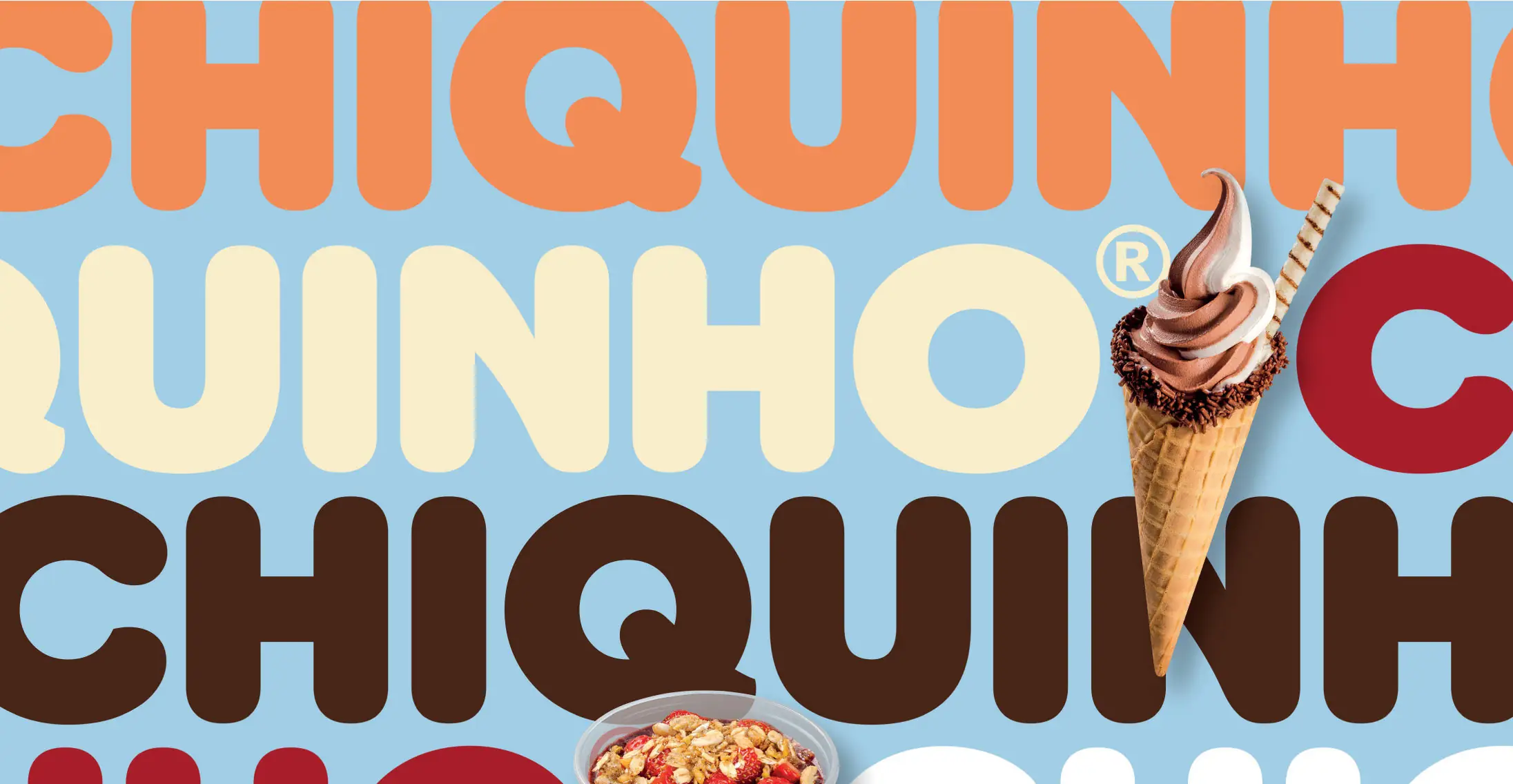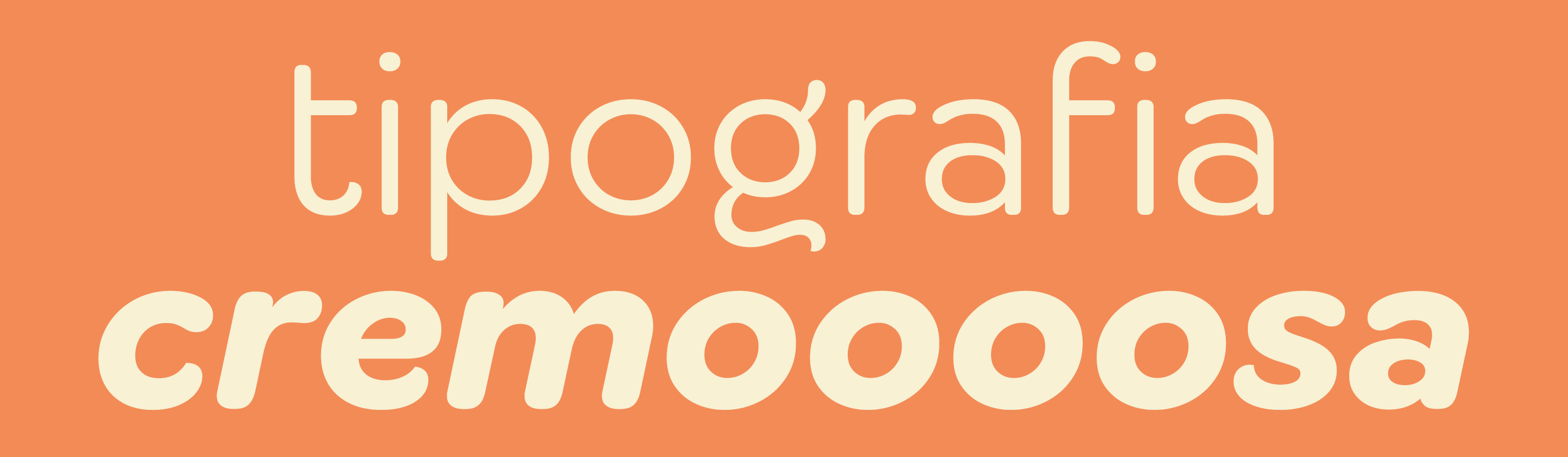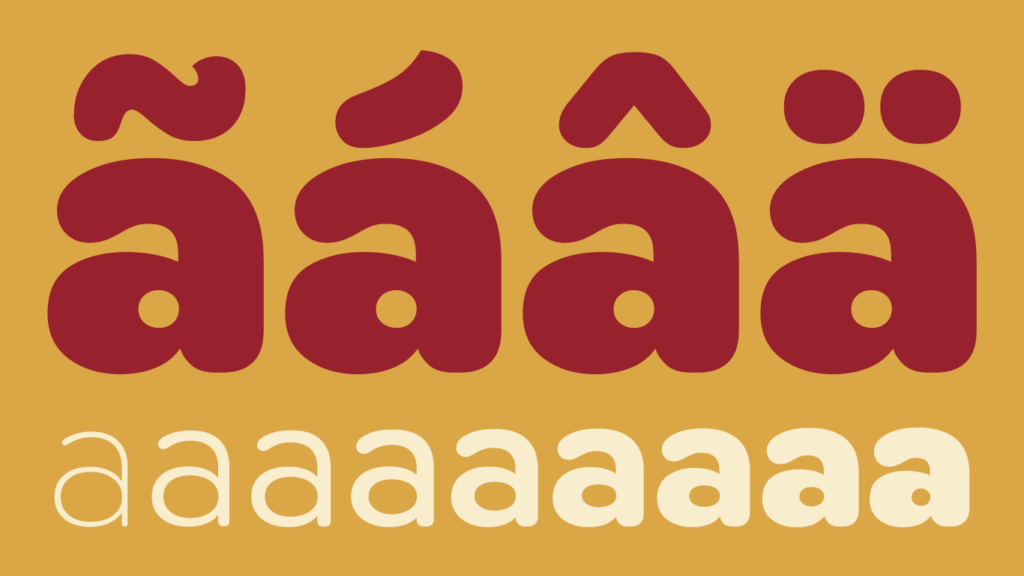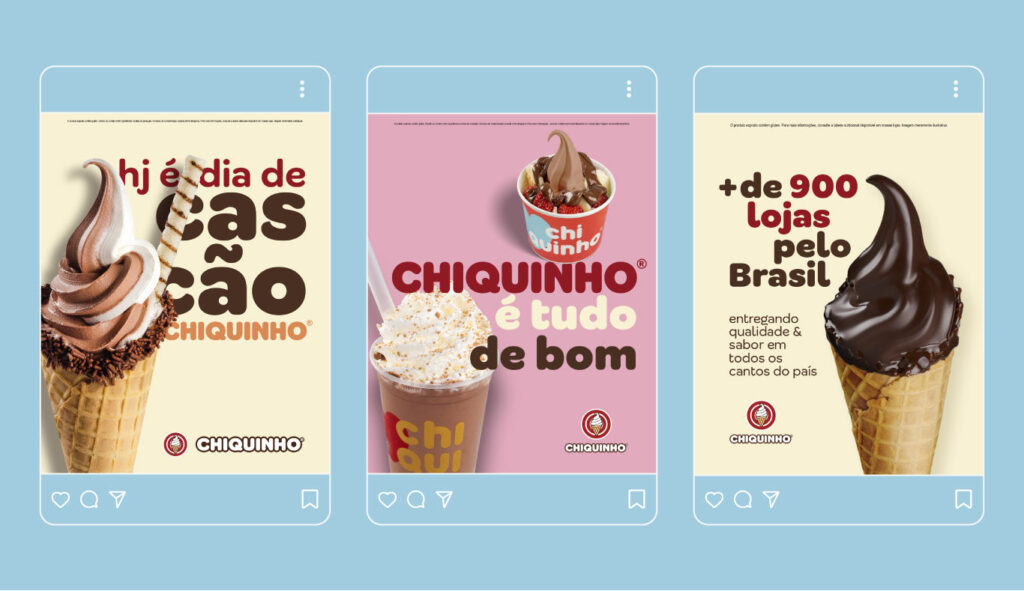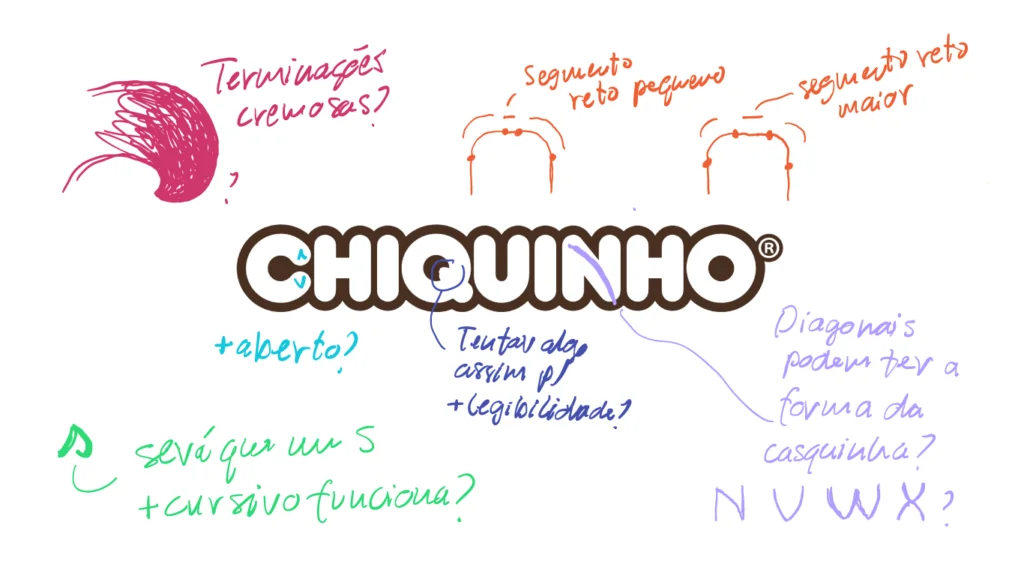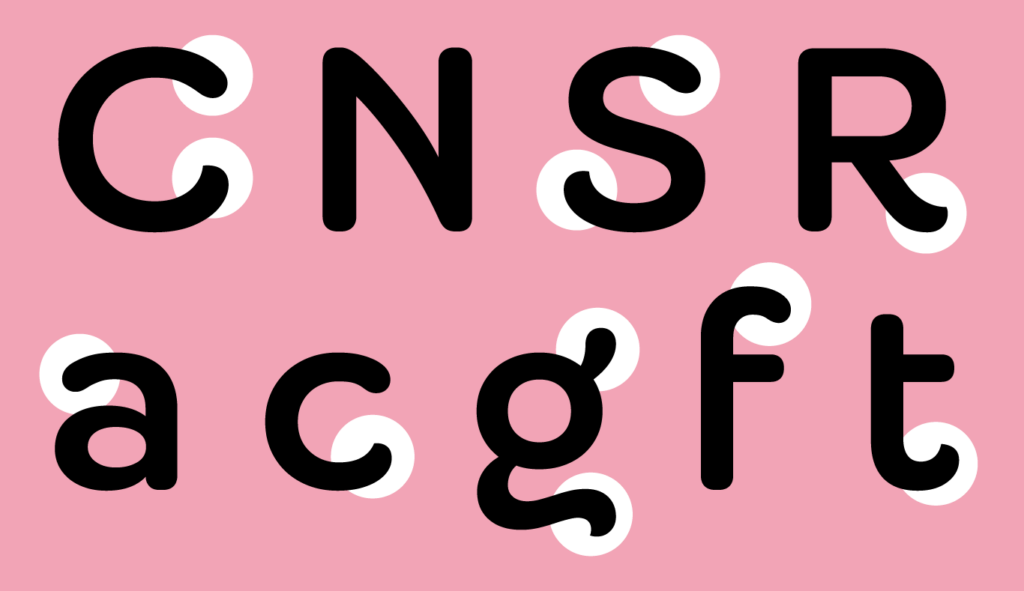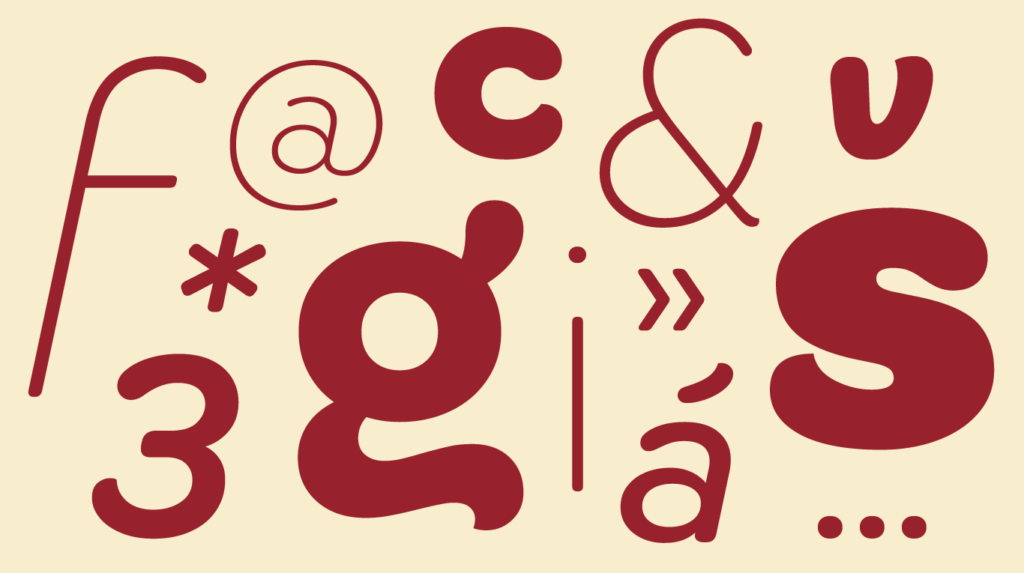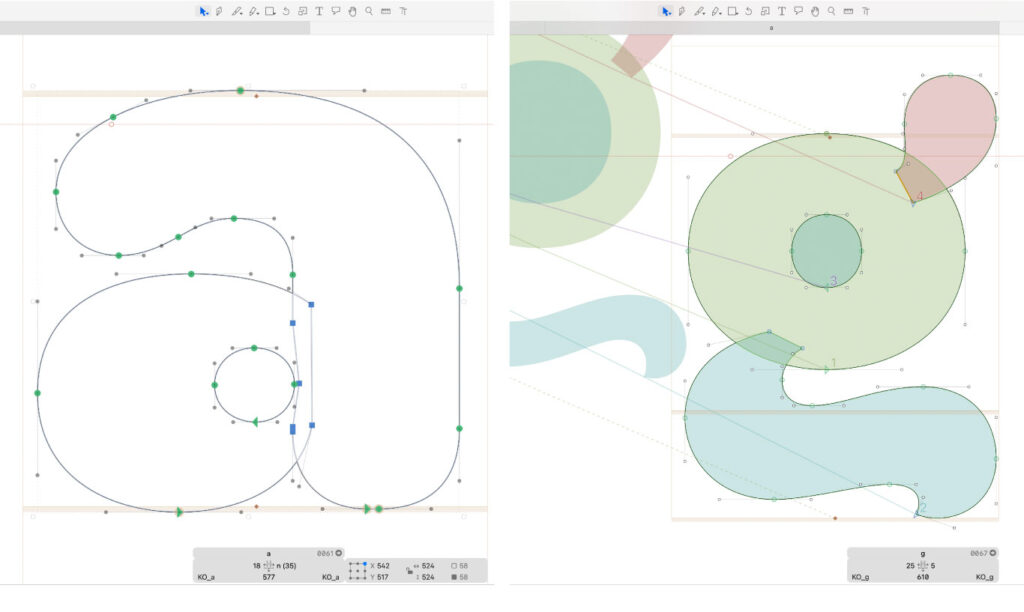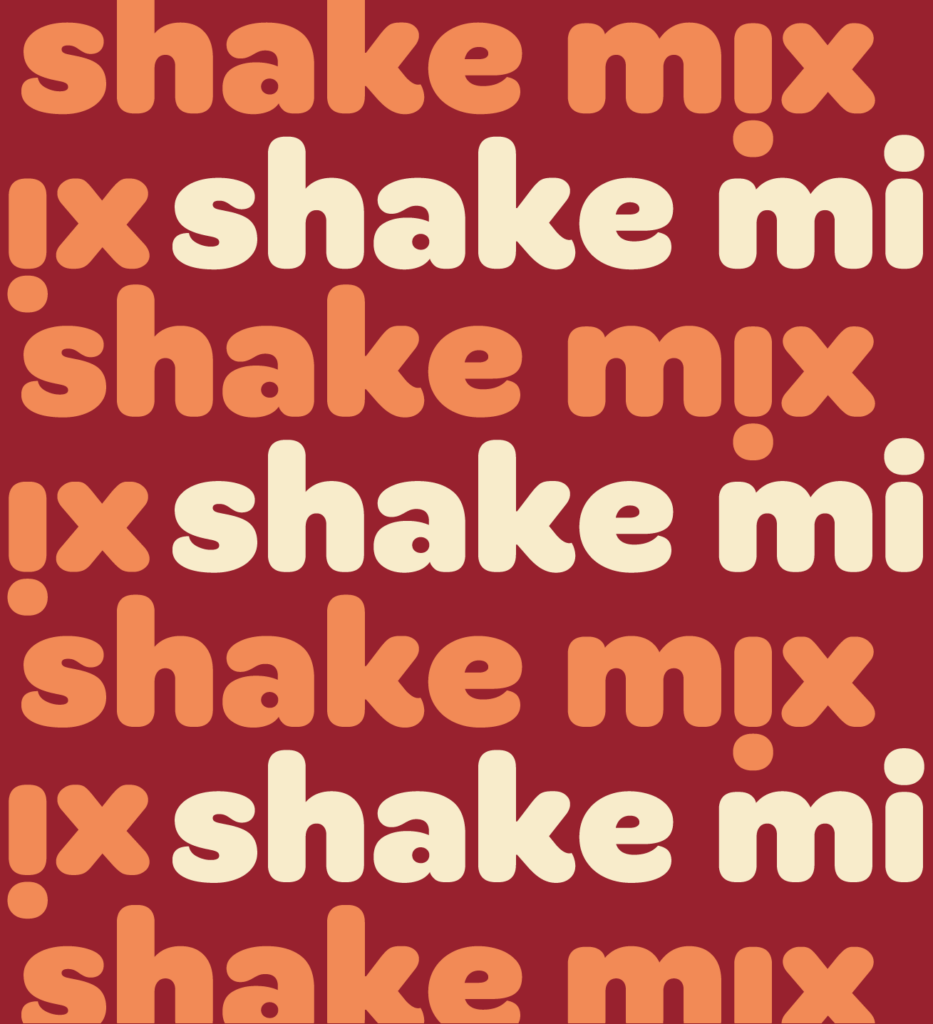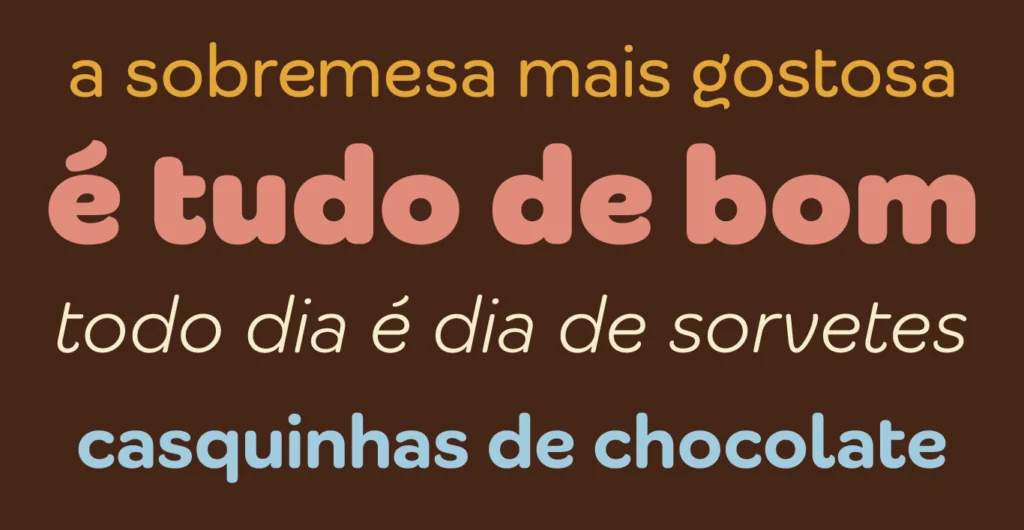
É hora de falarmos sobre a tipografia da Chiquinho
Para a maior rede de sorveterias do Brasil, desenvolvemos uma família tipográfica exclusiva que captura a essência popular e acessível da marca, mantendo a qualidade que sempre foi o compromisso da Chiquinho.
O desafio era criar uma tipografia especial, sob medida, que facilmente se conectasse com o público da Chiquinho. A solução veio através de um detalhe distintivo: as terminações das curvas superiores são delicadamente arredondadas, enquanto as inferiores formam pontas cremosas que remetem à textura do sorvete — trazendo a essência do produto para dentro do próprio desenho das letras, algarismos, símbolos e até na vírgula.
A letra ‘g’ é a nossa favorita, irresistível, para a surpresa de zero designers que nos acompanham. Até os acentos receberam o tratamento “cremoso”, com formatos que lembram pequenas gotas de sorvete — uma sutil surpresa quando descoberta.
A família tipográfica completa oferece 9 pesos em 2 estilos (Títulos e Textos), totalizando 18 fontes que dão flexibilidade à comunicação. A personalidade é mais pronunciada na versão para Títulos, ideal para chamar a atenção. Já na versão para Textos, várias letras foram sutilmente alteradas para garantir maior legibilidade em tamanhos reduzidos.
O resultado é uma tipografia que reflete a origem popular e acessível da marca, mas se mantém contemporânea e funcional em qualquer aplicação — das fachadas das lojas ao menu digital nas unidades mais modernas.
Para a Chiquinho, agora cada palavra escrita conecta o consumidor com a essência da marca, provando que o desenho específico das letras tem impacto significativo na percepção da marca e na experiência que começa muito antes da primeira colherada.